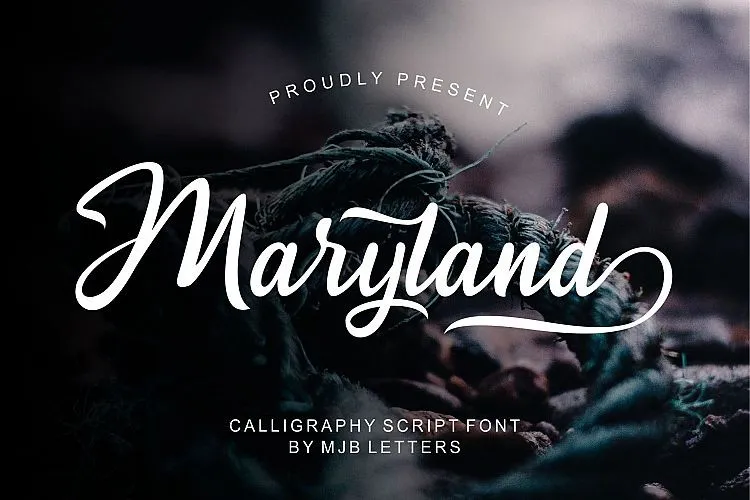
Maryland Calligraphy Font – Fonte Grátis
Maryland Calligraphy Font
A Maryland Font é uma fonte tipográfica em estilo script com influências de caligrafia. Perfeita para aqueles que buscam um toque elegante e moderno, esta fonte proporciona alegria através de suas linhas fluidas e variáveis baseline. Ela oferece uma forte presença visual, criada cuidadosamente a partir da arte da caligrafia. O lema deste design é o amor pelas características alternativas e as swashes inclusivas, que permitem criar designs personalizados únicos. Esta fonte traz estilo para qualquer projeto de design, seja ele branding (logotipo), criação de mensagens ou mesmo etiquetas de embalagem. Seja ela a fonte perfeita para suas necessidades de design, Maryland Font é uma escolha inteligente para quem busca expressar individualidade e elegância em seus trabalhos visuais.